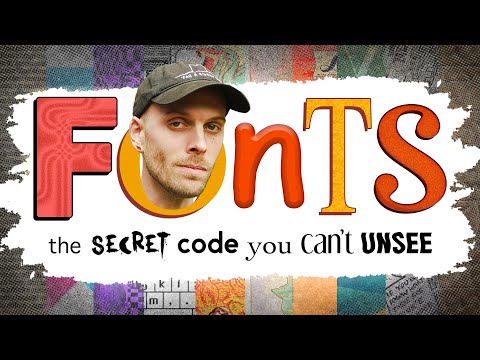
Unterhaltsame Zusammenfassung
Die Geschichte der Schriftarten
Struthless liefert einen astreinen Video Essay über die Geschichte von Fonts, also Schriftarten, ab. Dabei gibt es nicht nur einige interessante Hintergründe zu erfahren, sondern auch viele kreative Einfälle zu sehen, die einen insgesamt erstaunlich kurzweiligen Edit ergeben.
„Why do words look they way they do? That was the question that kicked this project off. I pulled at the thread, and it turns out the answer was way deeper than I thought…“